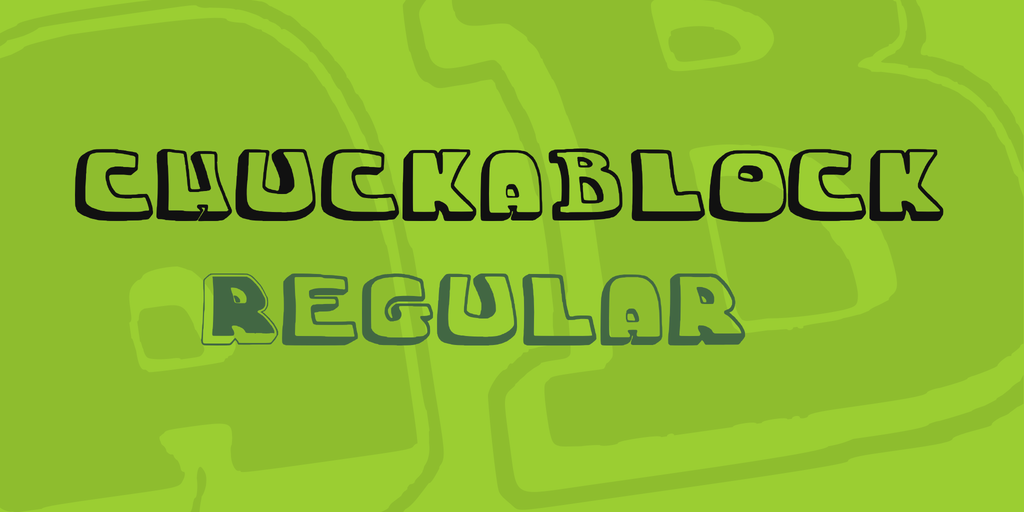
A Chuckablock Font é uma homenagem ao incrível trabalho do artista Chuck Stake, destacando seu estilo único e emocionante. Suas obras criativas podem ser encontradas no site www.oxygenartcentre.org/exhibition-chuck-stake/, onde você pode explorar diferentes expressões de sua arte vibrante. Inspirado nas características reconhecíveis de Chuck Stake, a Chuckablock Font oferece uma maneira visual de transmitir sua personalidade e estilo. Esta fonte é perfeita para designers que desejam incorporar um toque único e emocionante em suas criações digitais, mantendo fiel ao espírito inspirador de Chuck Stake.